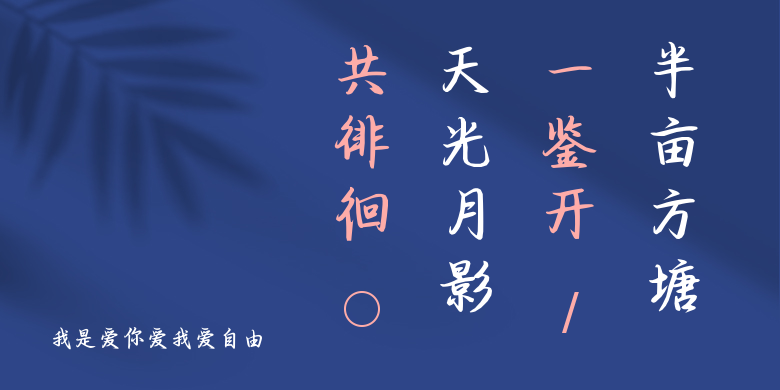
我是爱你爱我爱自由
我是爱你爱我爱自由,这款字体结构工整、笔画清晰,兼顾美观与易读性,适用于标题、正文、海报、包装、LOGO 等多种场景。字形优雅稳定,风格百搭耐看,适配日常排版与创意设计,让文字呈现更舒适、更具质感。我是爱你爱我爱自由一笔一画,皆是细节,以均衡的比例、流畅的线条打造舒适视觉体验,字形端正大气,风格简约现代。无论是商业设计、品牌宣传还是日常排版,都能轻松驾驭,让文字更有格调与力量。我是爱你爱我爱自由字体下载。